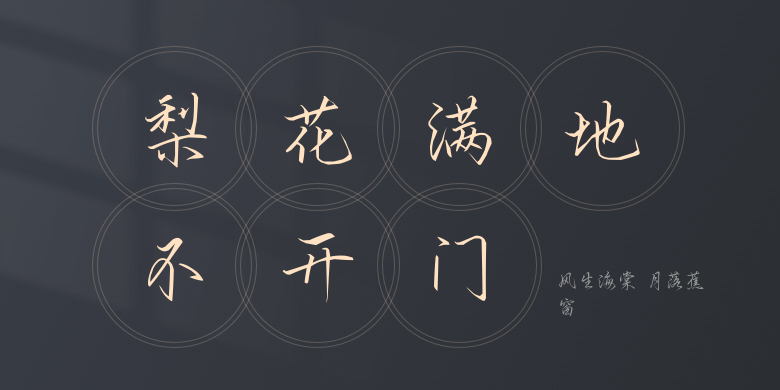
风生海棠 月落蕉窗
风生海棠 月落蕉窗,这款字体结构工整、笔画清晰,兼顾美观与易读性,适用于标题、正文、海报、包装、LOGO 等多种场景。字形优雅稳定,风格百搭耐看,适配日常排版与创意设计,让文字呈现更舒适、更具质感。风生海棠 月落蕉窗一笔一画,皆是细节,以均衡的比例、流畅的线条打造舒适视觉体验,字形端正大气,风格简约现代。无论是商业设计、品牌宣传还是日常排版,都能轻松驾驭,让文字更有格调与力量。风生海棠 月落蕉窗字体下载。